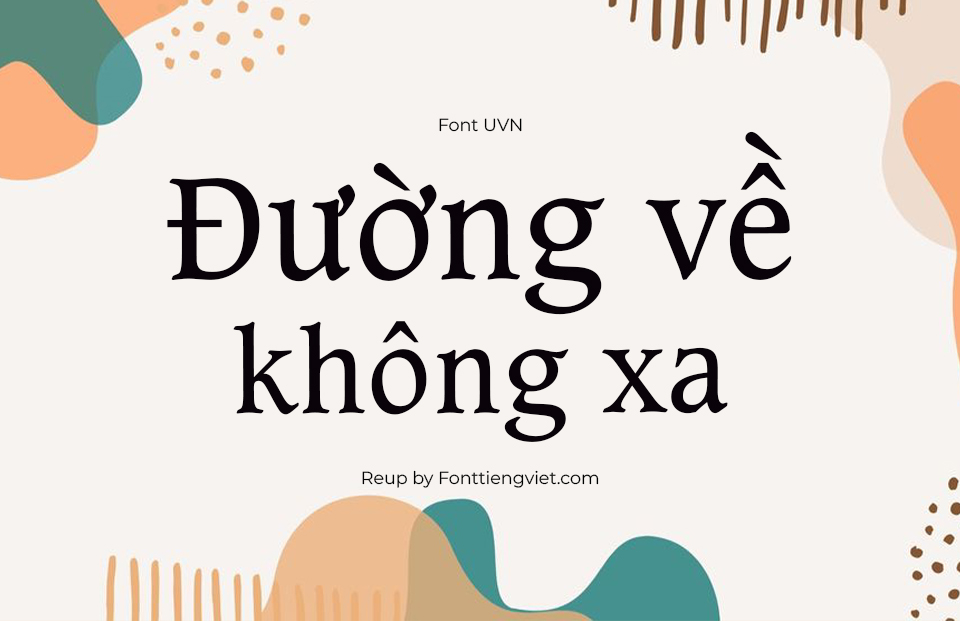
Giới thiệu về Font Việt Hóa UVN Cat Bien
Trong thế giới đồ họa, việc lựa chọn một Font Chữ phù hợp đóng vai trò quan trọng trong việc truyền tải thông điệp. Font Việt Hóa UVN Cat Bien là một trong những bộ font tiêu biểu thuộc hệ thống UVN, được thiết kế tối ưu cho ngôn ngữ tiếng Việt với các dấu thanh chuẩn xác và thẩm mỹ cao. Với nét chữ mềm mại nhưng vẫn giữ được sự rõ ràng, bộ font này đã trở thành lựa chọn ưu tiên cho các thầy cô giáo và học sinh sinh viên khi trình bày tài liệu học tập hoặc các bài thuyết trình chuyên nghiệp.
Đặc điểm nổi bật của font chữ
Đặc trưng của bộ chữ này nằm ở sự thanh thoát, mang lại cảm giác dễ chịu cho người đọc. Font Việt Hóa UVN Cat Bien không chỉ đảm bảo tính hiển thị tốt trên các phần mềm soạn thảo văn bản như Word mà còn hoạt động mượt mà trên các công cụ thiết kế chuyên dụng như Photoshop hay Canva. Điều này giúp người dùng dễ dàng tạo ra các ấn phẩm đẹp mắt mà không lo lỗi font hay sai lệch khoảng cách chữ.
Ứng dụng Font Việt Hóa UVN Cat Bien trong học tập
Nhờ phong cách tối giản và gần gũi, bộ font này thường được ứng dụng rộng rãi trong môi trường giáo dục. Giáo viên có thể sử dụng để thiết kế slide giảng dạy, bảng tin lớp học hoặc các chứng chỉ khen thưởng cho học sinh. Bên cạnh đó, các bạn học sinh cũng có thể dùng font chữ này để trang trí báo tường hoặc làm portfolio cá nhân thêm phần ấn tượng và sáng tạo hơn.